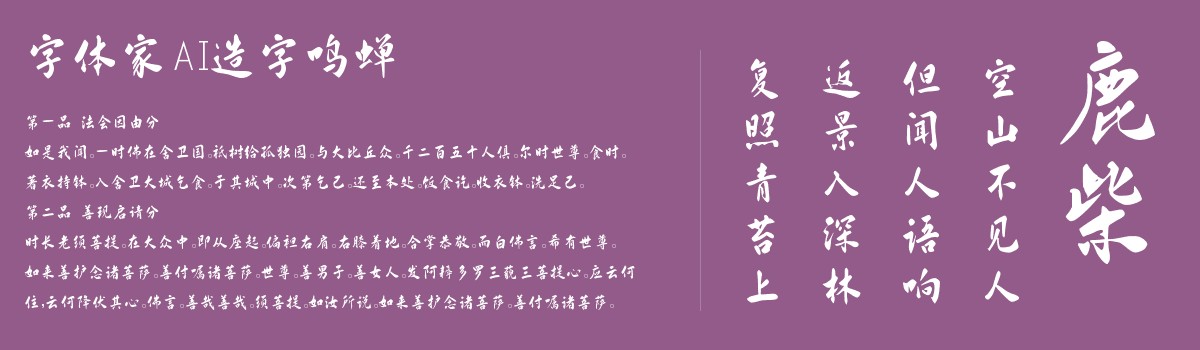
字体家AI造字鸣蝉
字体家AI造字鸣蝉是一款由字体家AI神笔造字生成的艺术字体,这款字体似手写墨迹,笔画流畅舒展,无机械刻板感。起笔收笔圆润柔和,无尖锐棱角,如指尖轻划纸面般自然。线条粗细有微妙变化,横画略轻、竖画稍重,撇捺舒展却不张扬,似微风拂柳般灵动。结构疏密得当,笔画间过渡衔接自然,无生硬转折,像连贯的呼吸般顺畅。整体气质温润亲切,既有手写的温度感,又不失工整,如友人手书般平和,无距离感,透着自然的韵律美。适合用于一些广告标题、平面文案、海报标题、网页广告用字的编辑。